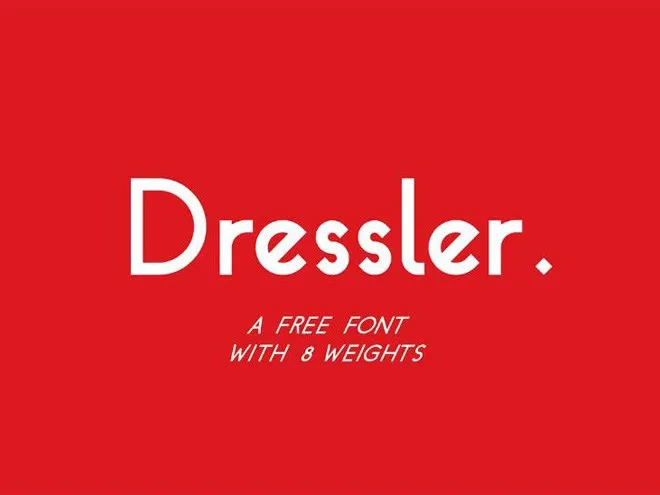
Esta fonte ‘Dressler Font Family’ foi desenvolvida pelo designer Hamilton e é uma família de tipo sans-serif moderna e clara. Esta combinação única de elegância e modernidade torna-a perfeita para qualquer projeto onde desejas que sua tipografia seja notável, mas não muito chata. Com 8 diferentes pesos disponíveis, você tem a liberdade de escolher o melhor em cada situação – daquela letra mais suave até um gosto por um estilo mais forte e agressivo. A fonte ‘Dressler Font Family’ oferece uma variedade de opções para que você possa expressar seu design de forma única. Essa família de tipo é perfeita para criações digitais, desde a sua logo ou site, até os seus materiais de marketing impressos. Compreende-se a importância da legibilidade, e esta fonte garante que será fácil ler em qualquer formato. E se você está procurando uma opção mais casual ou um pouco mais suave? A ‘Dressler Font Family’ também oferece uma versão redonda do mesmo estilo, ideal para dar um toque especial a textos que buscam a leveza e sofisticação. Obrigado por explorar Dressler; esperamos que ele se torne um importante membro de sua paleta de fontes.